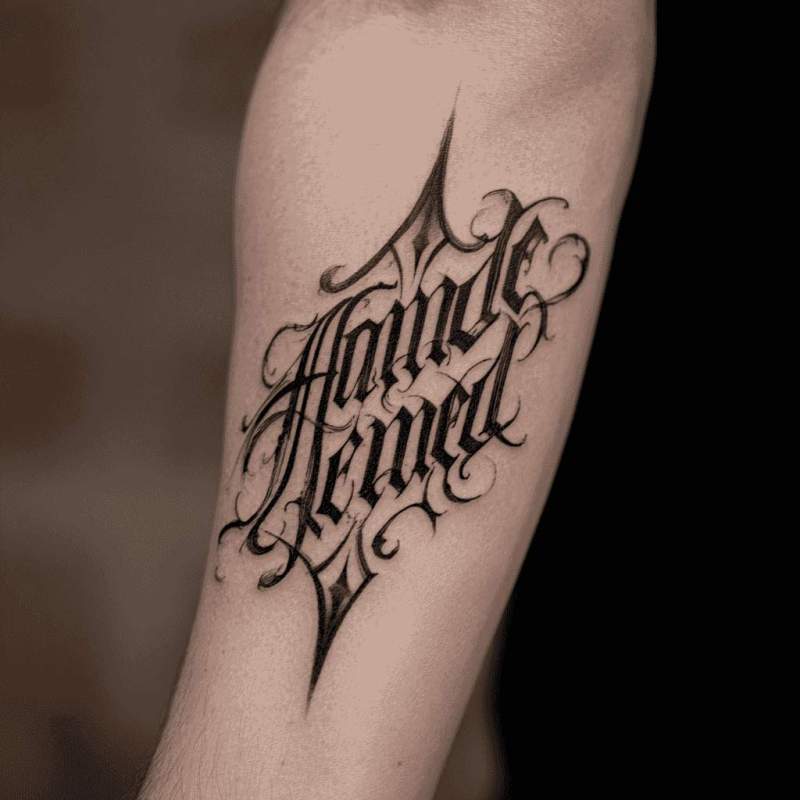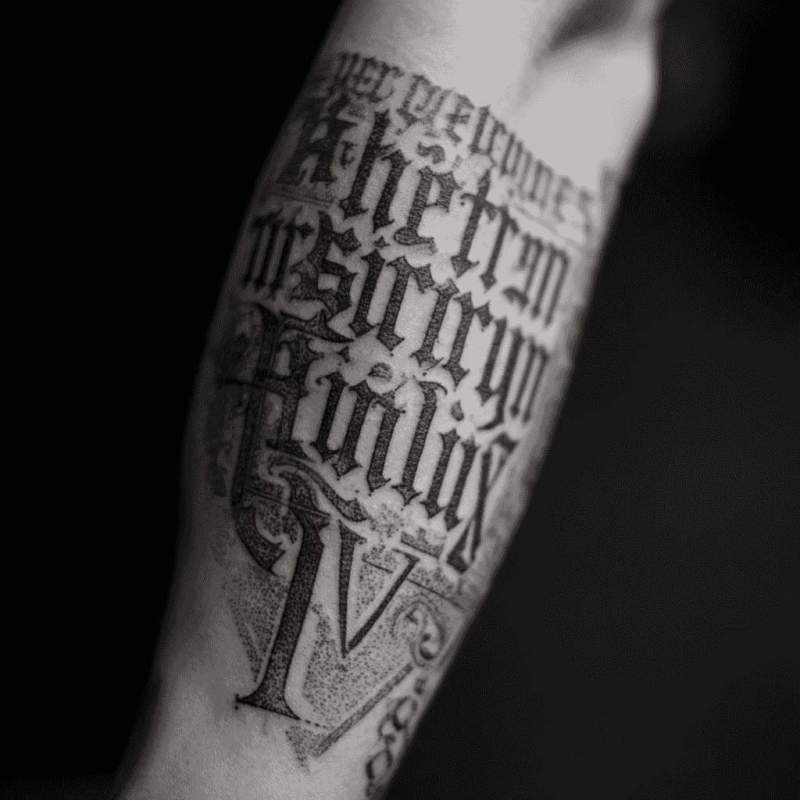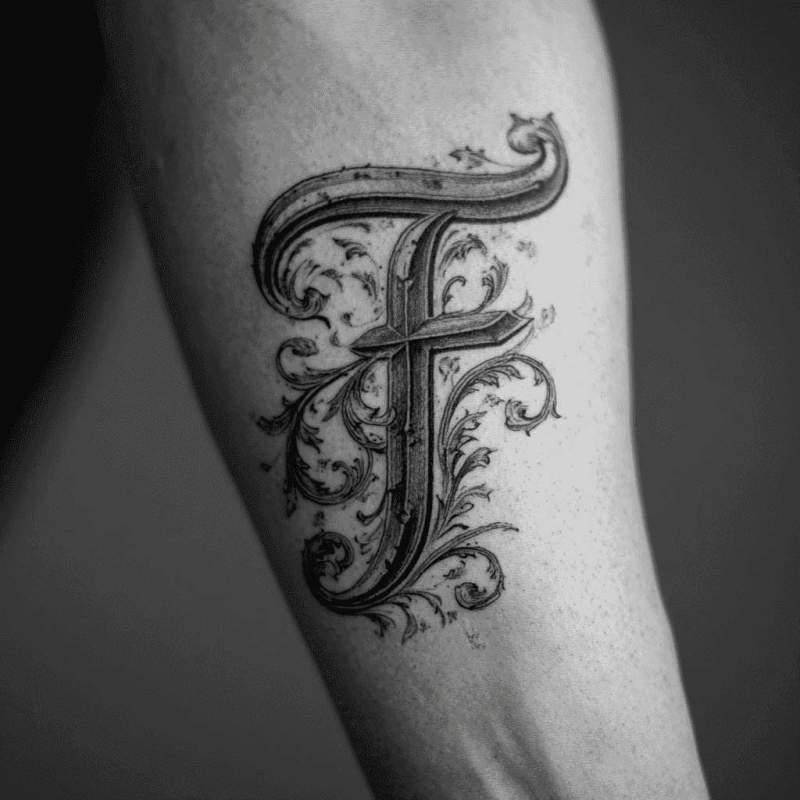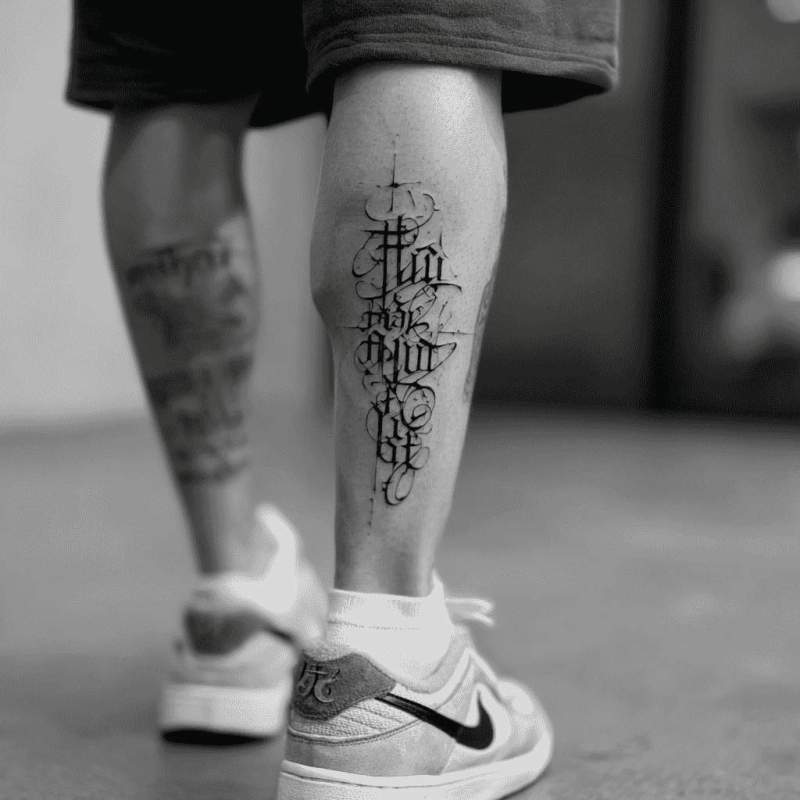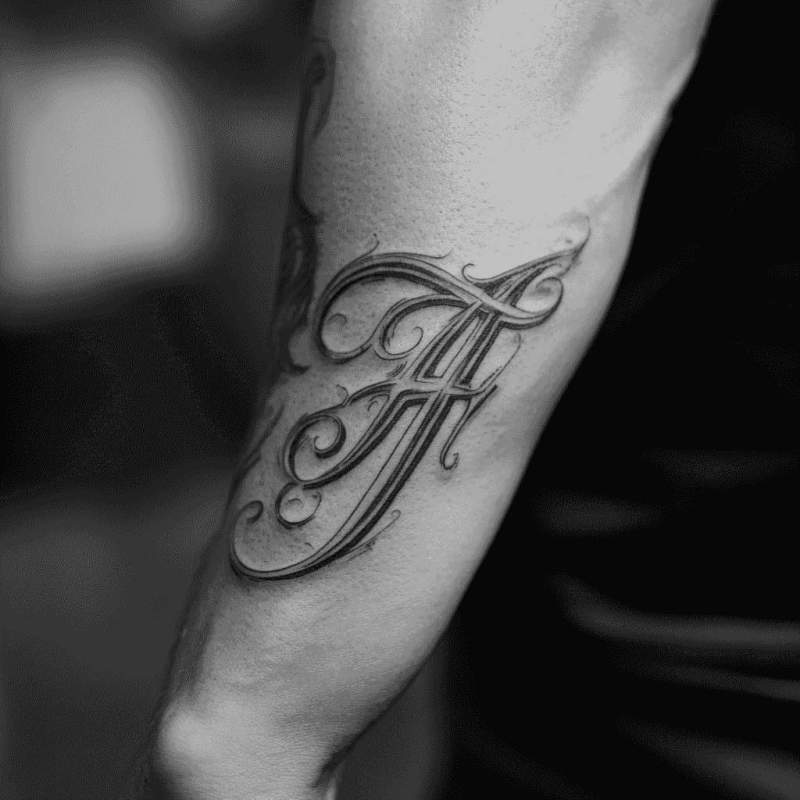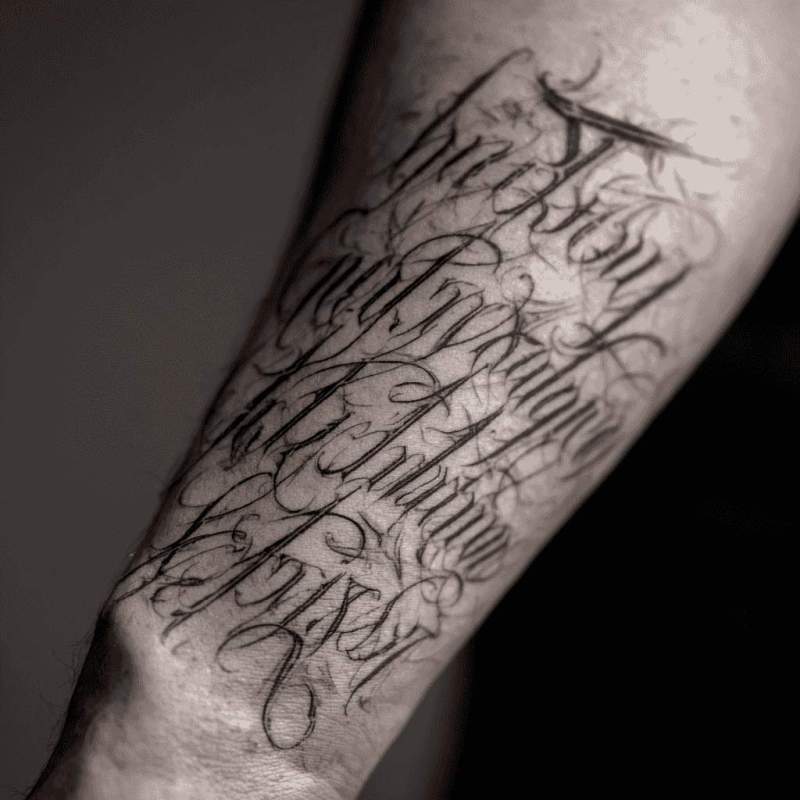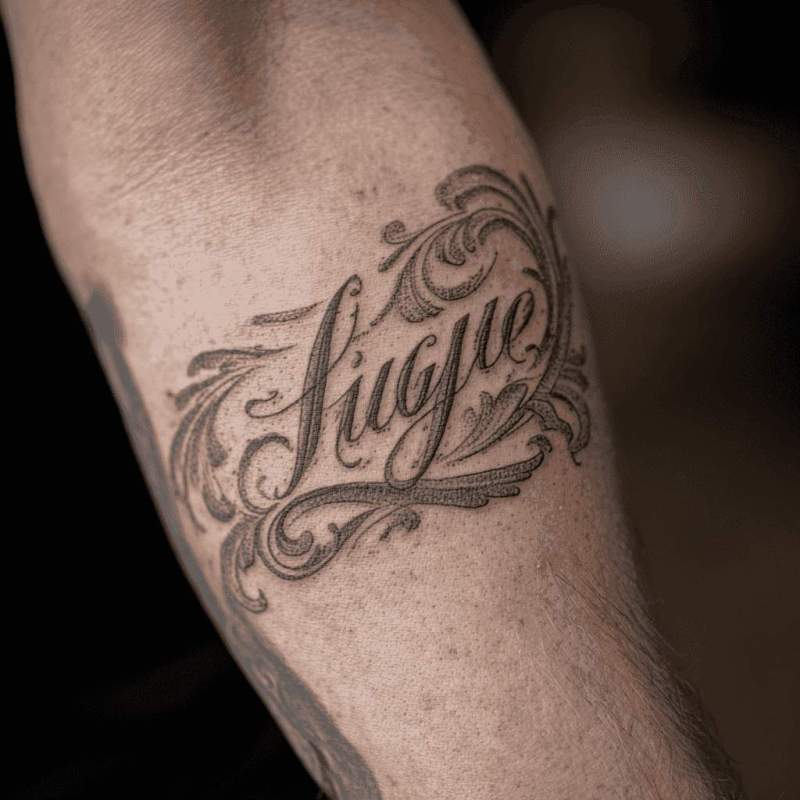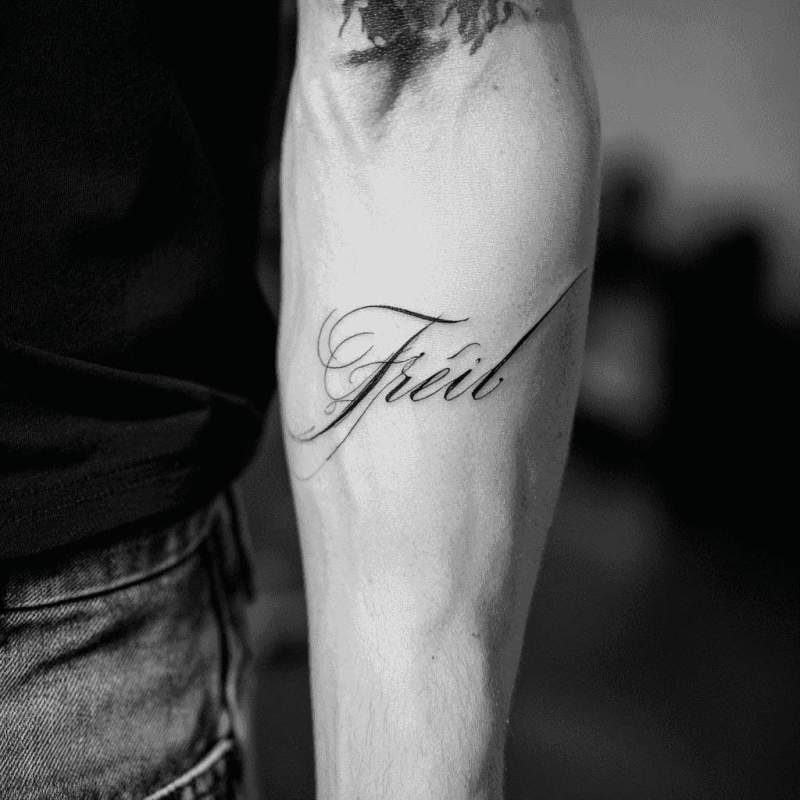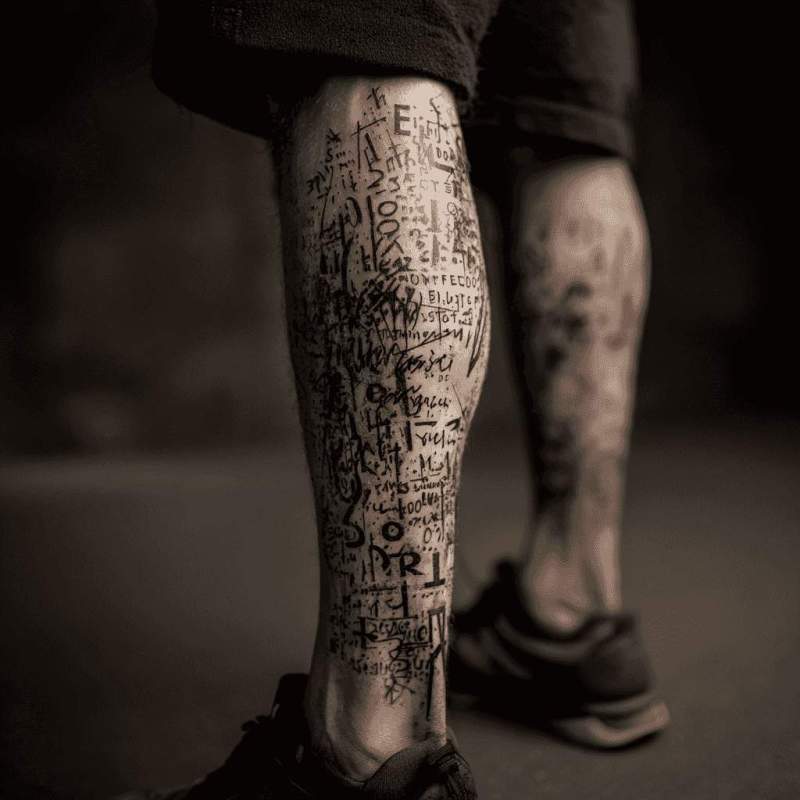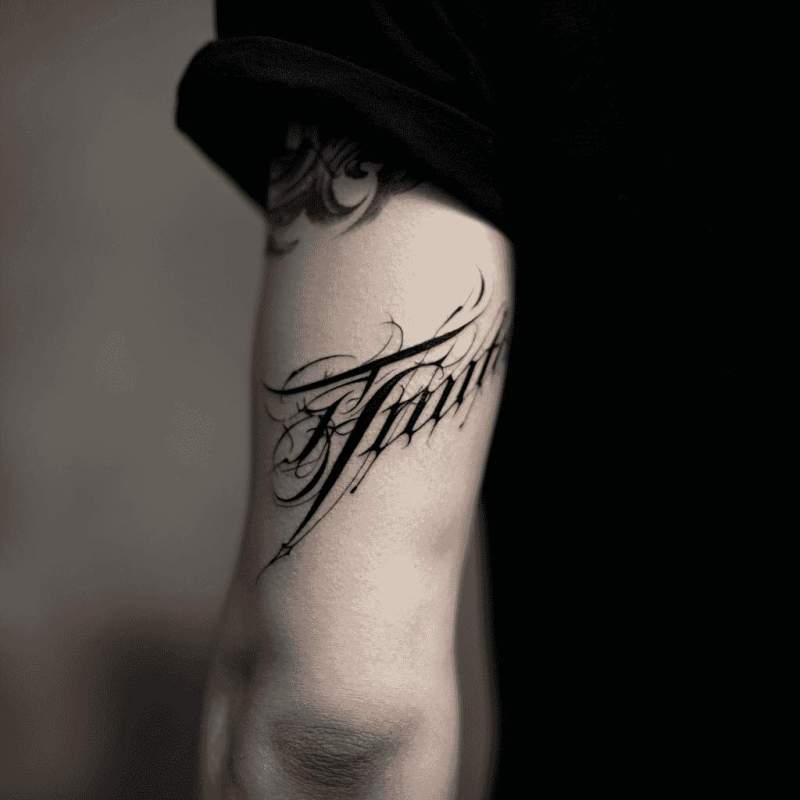
Magst du außergewöhnliche Schriftarten? Die Schrift-Tattoo-Künstler bei Lebende Legend in Bern, Schweiz haben die stylischsten Font-Designs zusammengetragen, um dir typografische Schrift-Inspiration zu verschaffen.
Tattoo-Schriftarten symbolisieren die Macht der Worte und persönliche Kommunikation. Sie repräsentieren Identität, Überzeugungen und wichtige Botschaften. Die Wahl der Schriftart kann Persönlichkeit ausdrücken: elegant, rebellisch, traditionell oder modern. Schrift-Tätowierungen machen abstrakte Konzepte sichtbar und permanent.